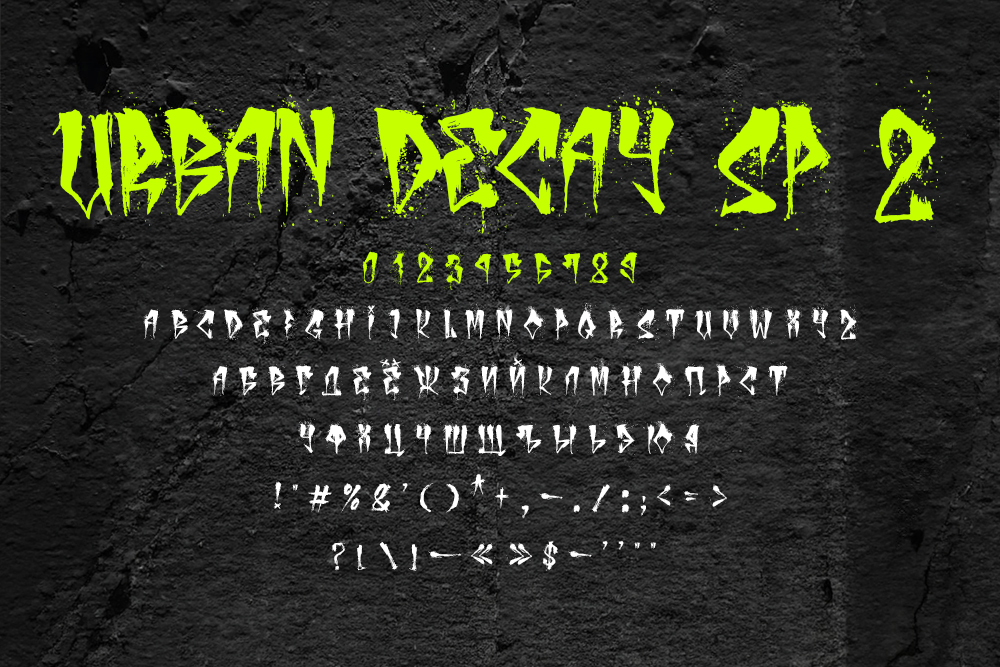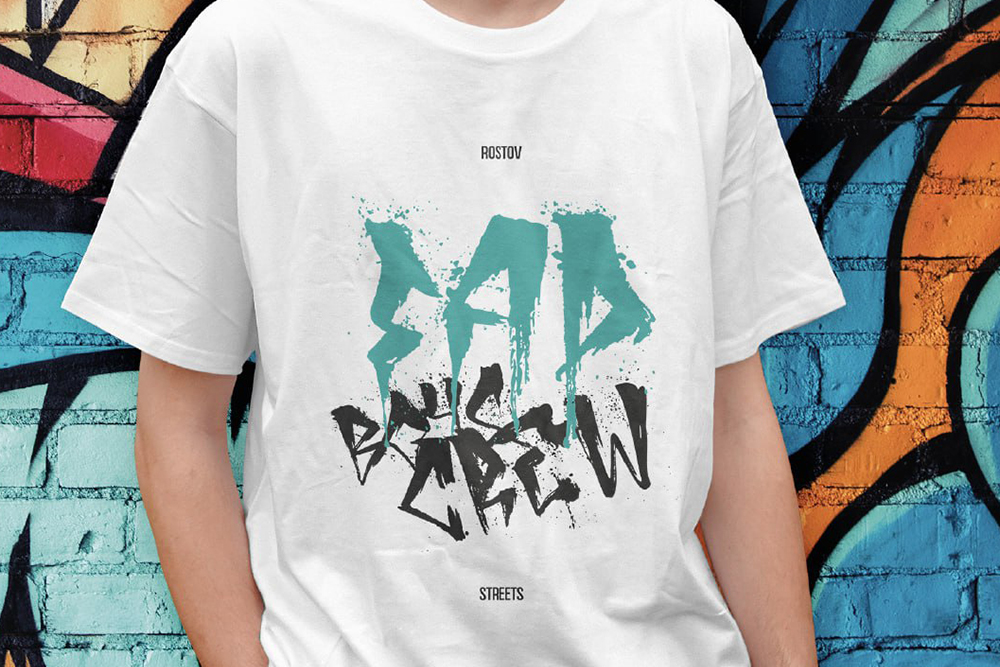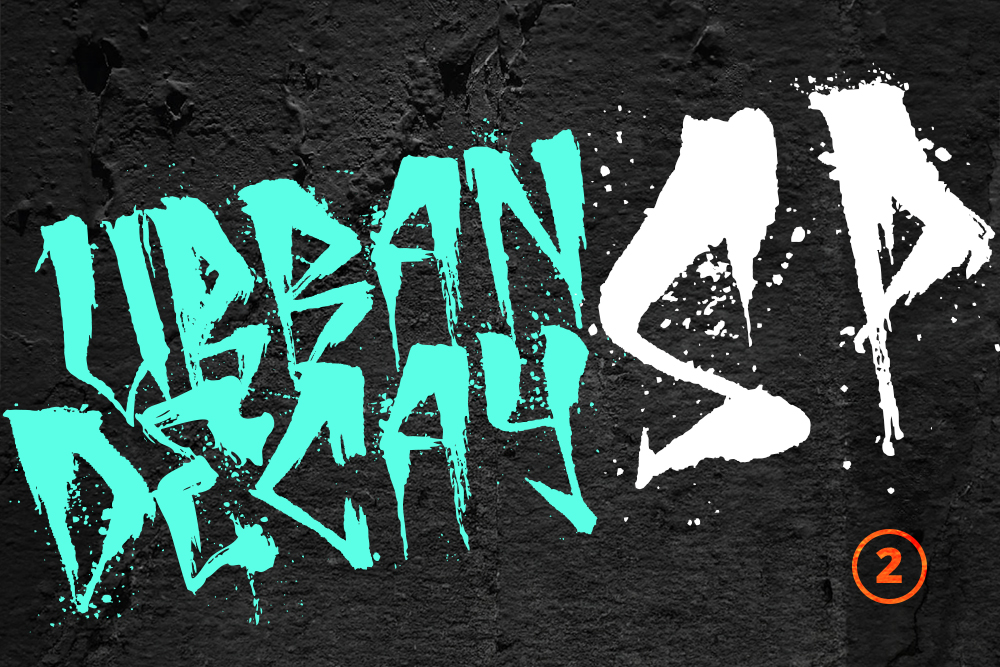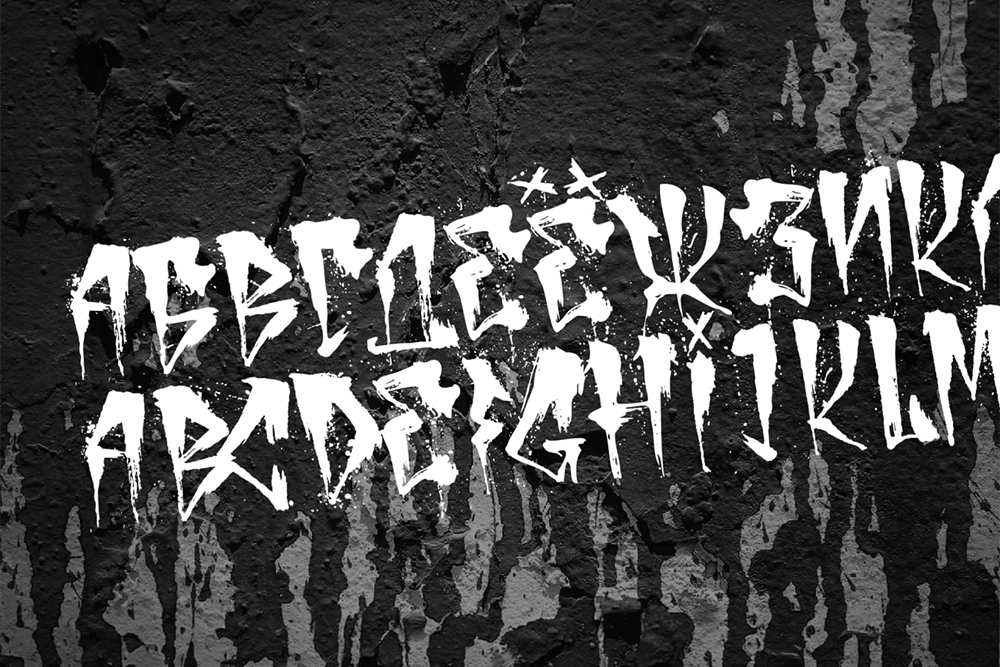
Шрифт Городской
Urban Decay — рваный кистевой штрих, острые углы, потёки и брызги, неровная посадка знаков: надпись будто сделана наспех по сырой городской стене. Кириллицу строили по мотивам латинского Urban Decay от zofos, стараясь не растерять напор оригинального рисунка. Постеры, обложки, музыкальные визуалы, мерч и молодёжная графика принимают его как шумный неформальный акцент. В комплекте — полная версия STAR и лицензия.